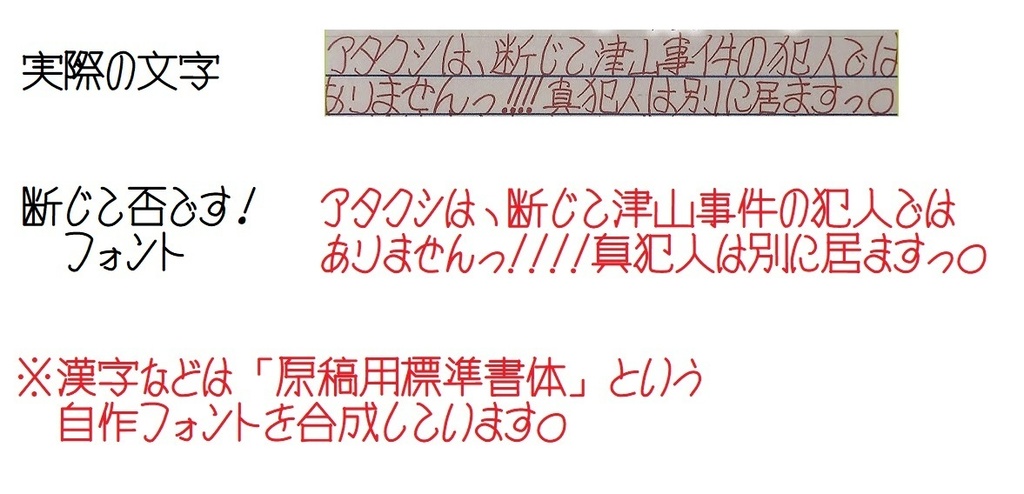
断じて否です!フォント
断(だん)じて否(いな)です!フォント
このフォントは、津山事件の勝●州彦容疑者の手紙の字を参考に、
ひらがな、カタカナ、数字をものまねしたフォントです。
収録文字:ひらがな、カタカナ、全角数字、句読点。
半角英数や漢字などは、自作フォント「原稿用標準書体」を使用しています。